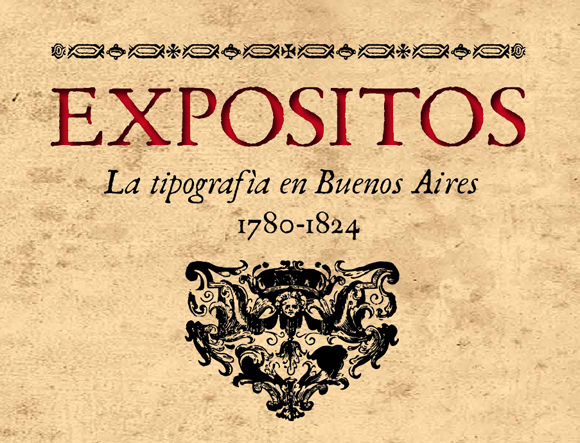
Fabio Ares, diseñador en comunicación visual, docente e investigador de la Universidad Nacional de La Plata, República Argentina, nos presenta la segunda edición de su obra Expósitos. La tipografía en Buenos Aires. 1780-1824, editada por la DG Patrimonio e Instituto Histórico de la Ciudad de Buenos Aires
En esta obra el autor nos propone un recorrido histórico de la imprenta hacia Buenos Aires, el desarrollo del arte tipográfico en la Imprenta de Niños Expósitos, pionera en el arte a partir de 1780 hasta su cierre en 1824. Además, el libro incluye una experiencia tipográfica que recrea en formato digital tres conjuntos de caracteres (redonda, cursiva y viñetas), diseñados a partir de documentos impresos originales, y que también fueron utilizados en su maquetación.